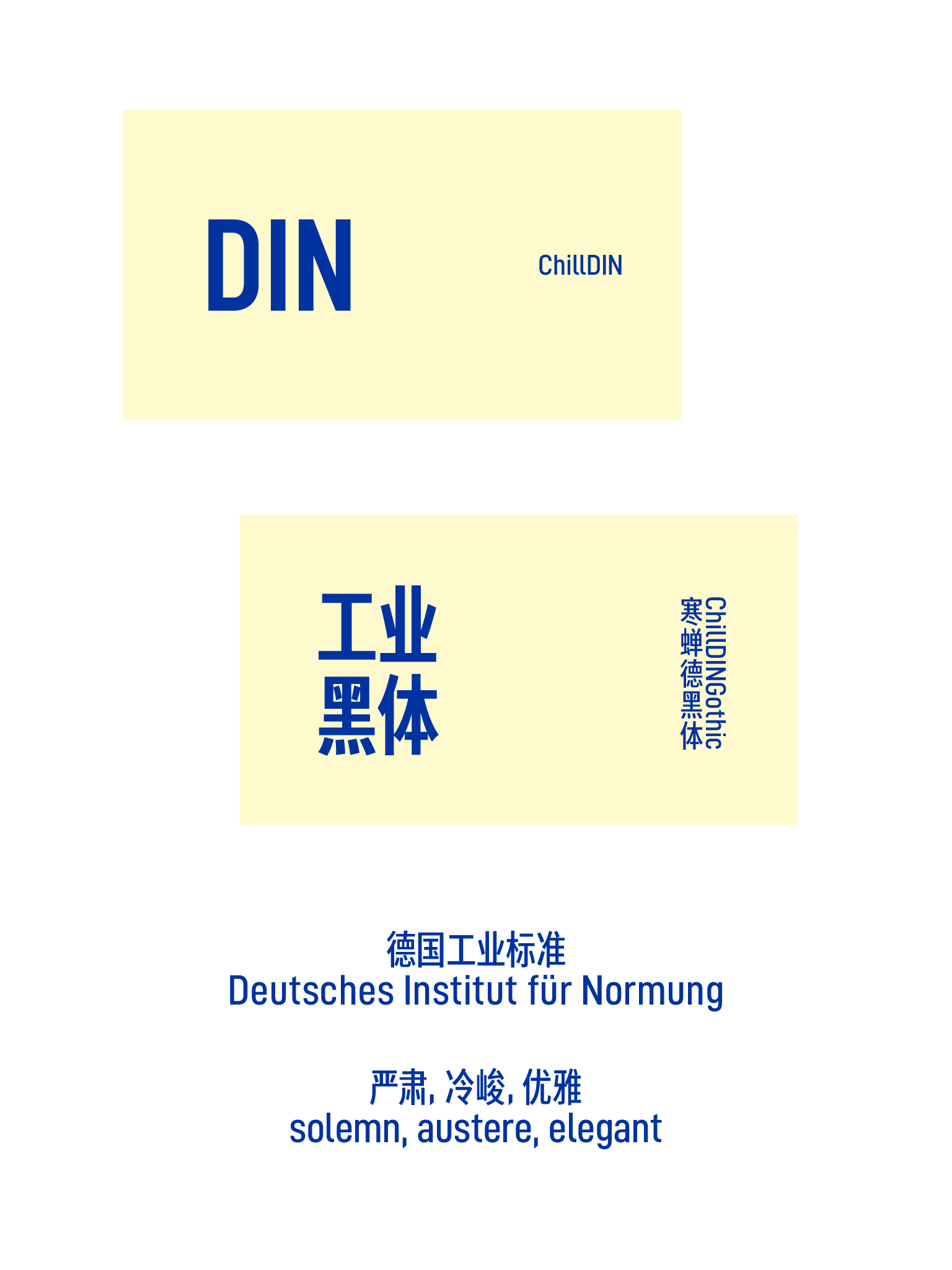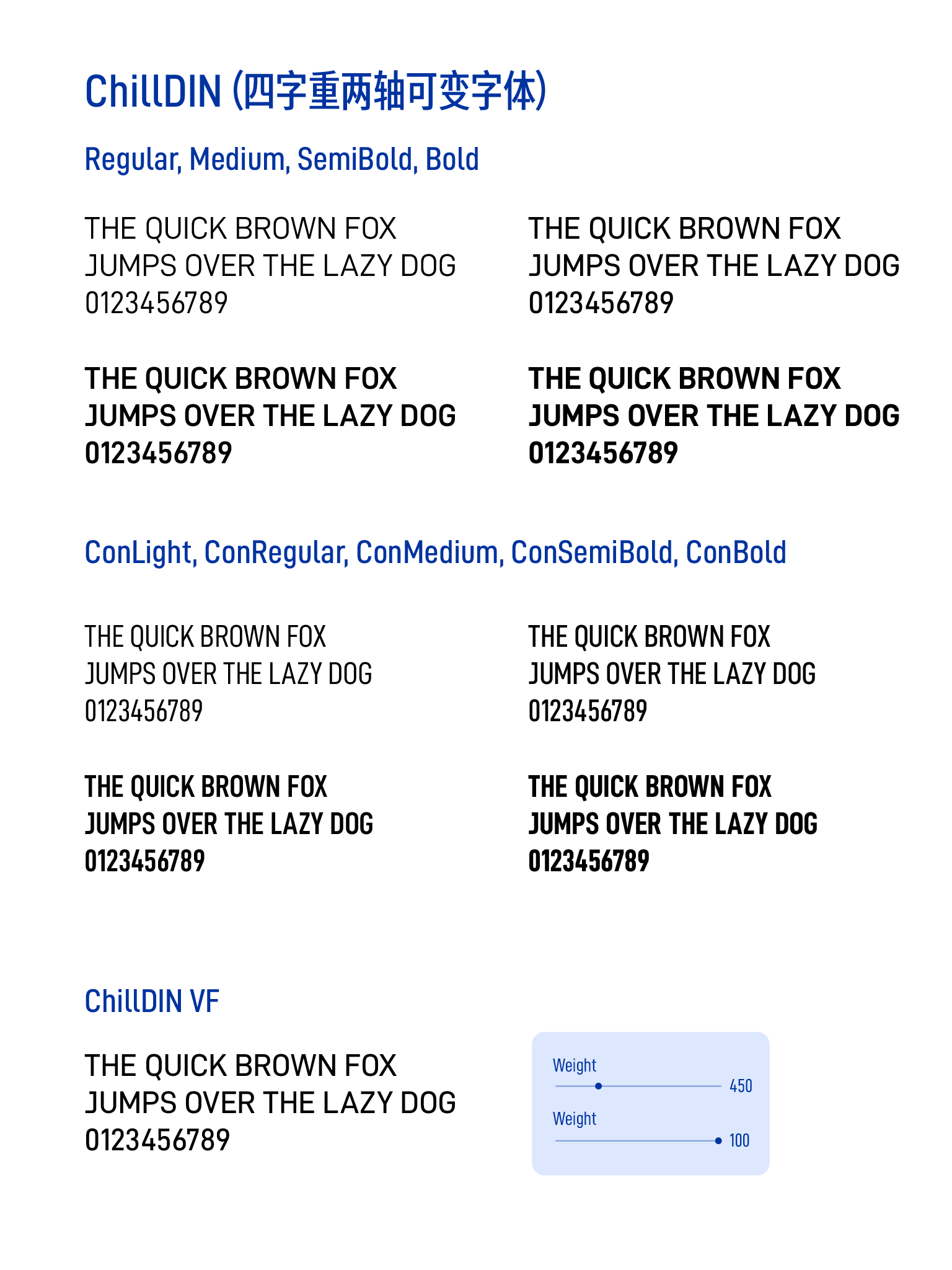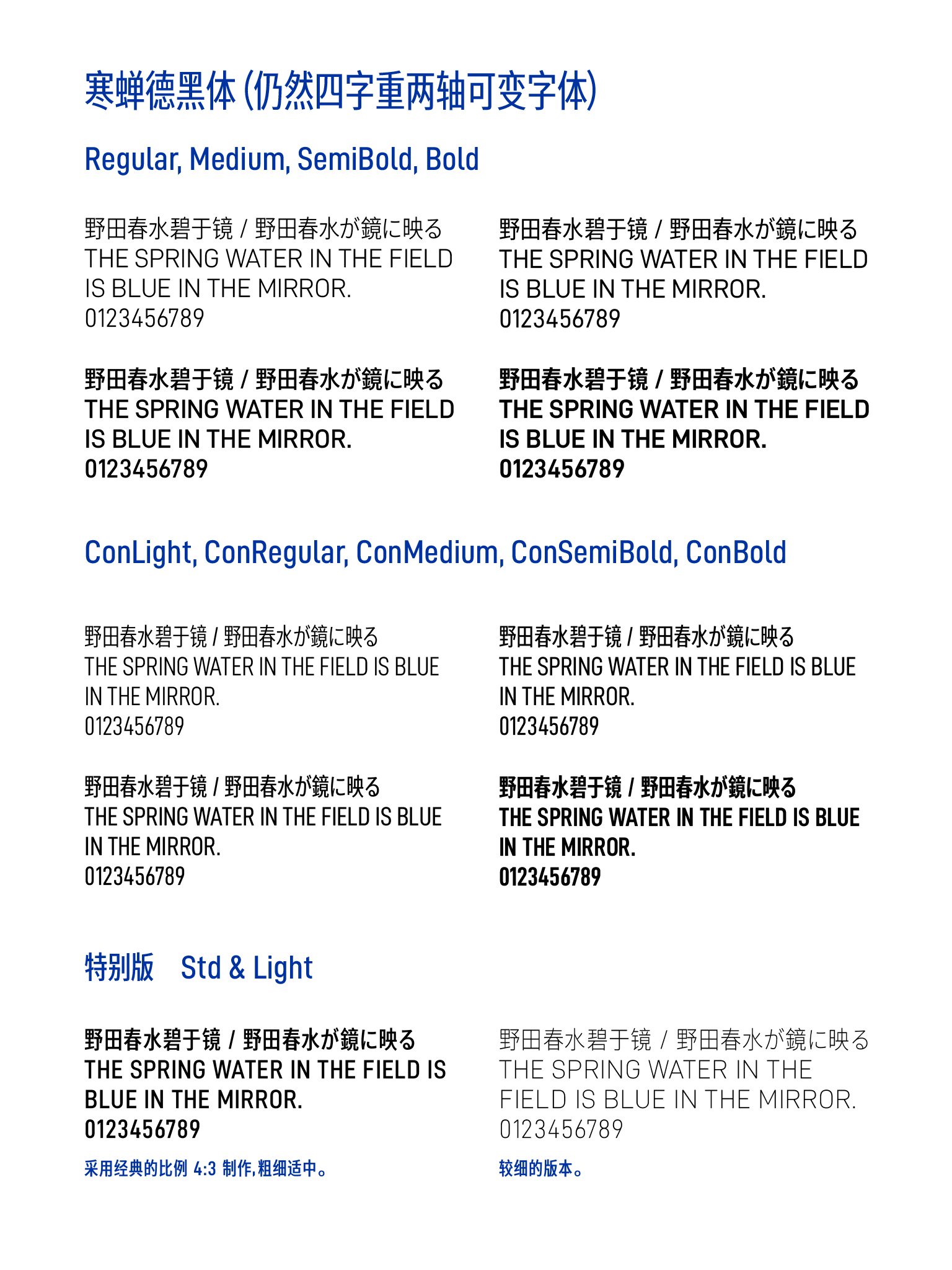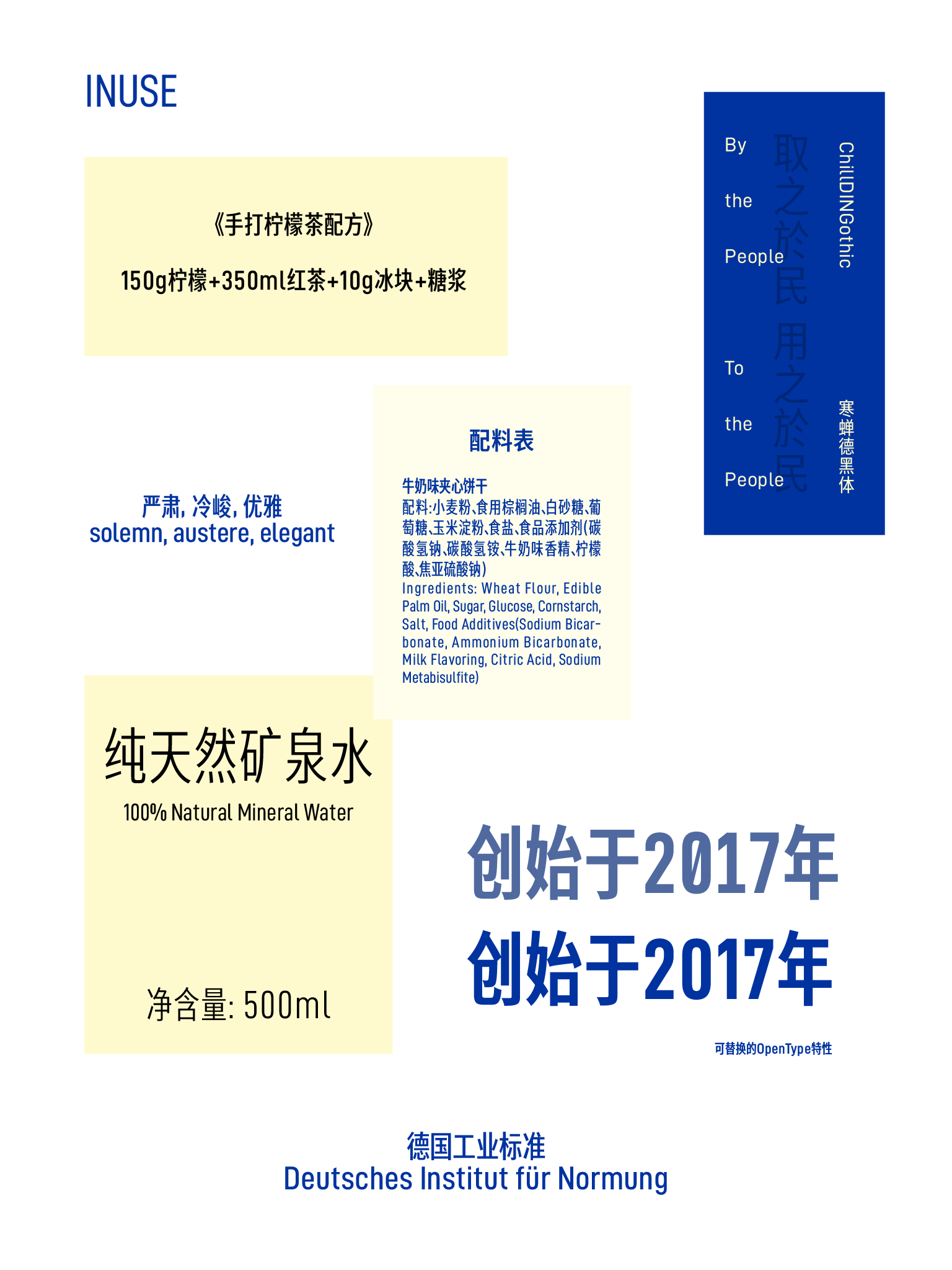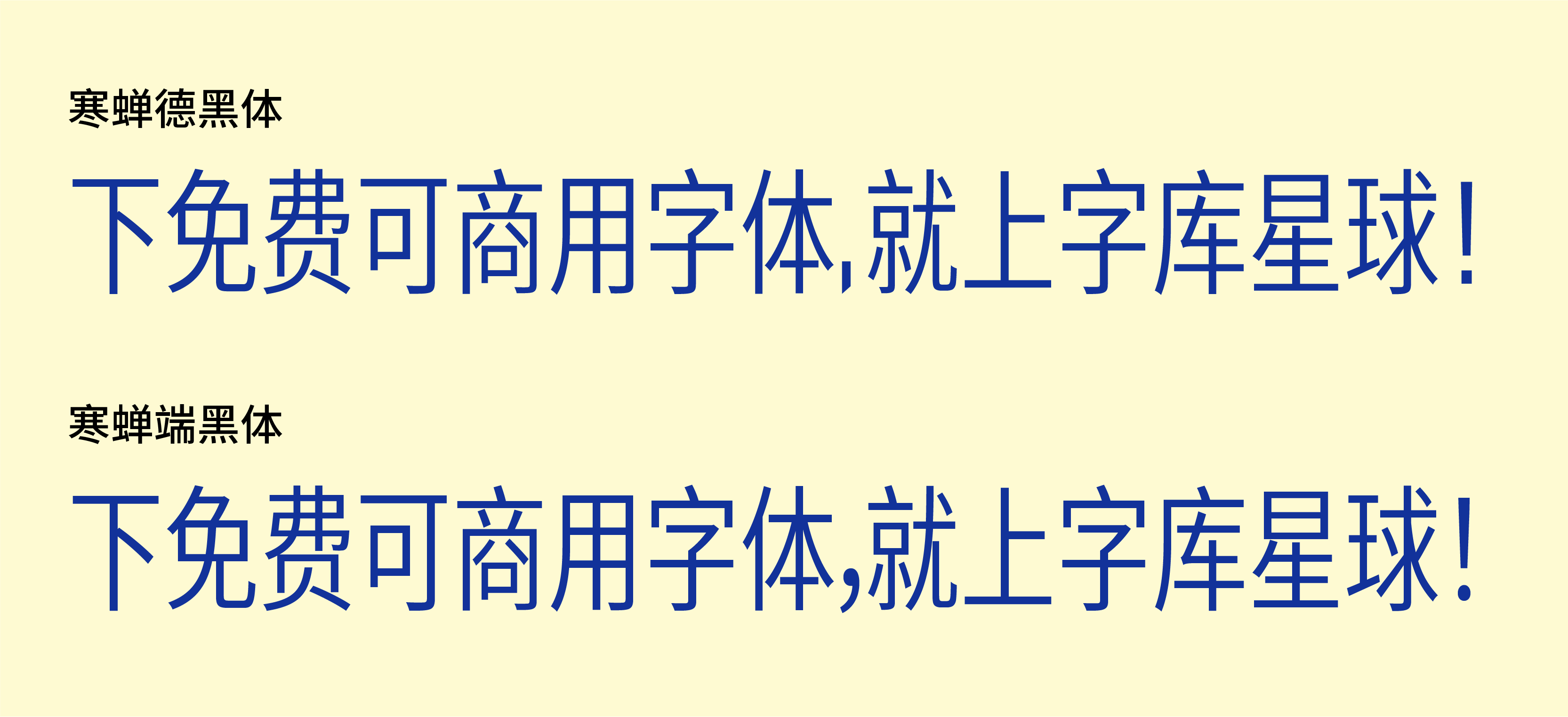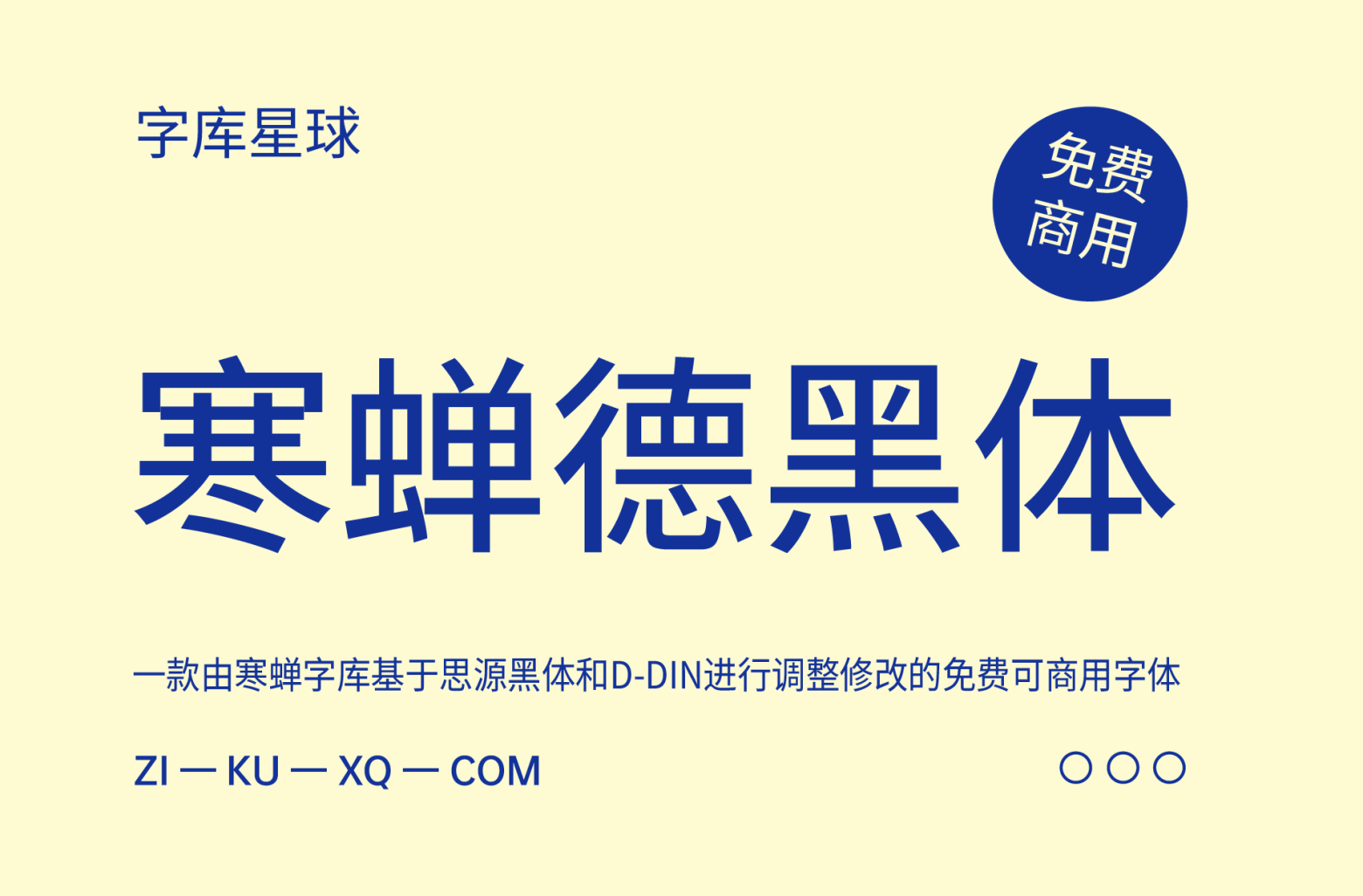
寒蝉德黑体
寒蝉德黑体是一款由寒蝉字库基于思源黑体和D-DIN进行调整修改的免费可商用字体。
ChillDIN与寒蝉德黑体。源于德国工业标准字体“DIN”,基于D-DIN的修缮。中文字体的搭配从来源寒蝉端黑体(思源黑体),修改了参数和标点融合。
寒蝉德黑体和寒蝉端黑体两者的区别之处:修改了参数和标点融合。